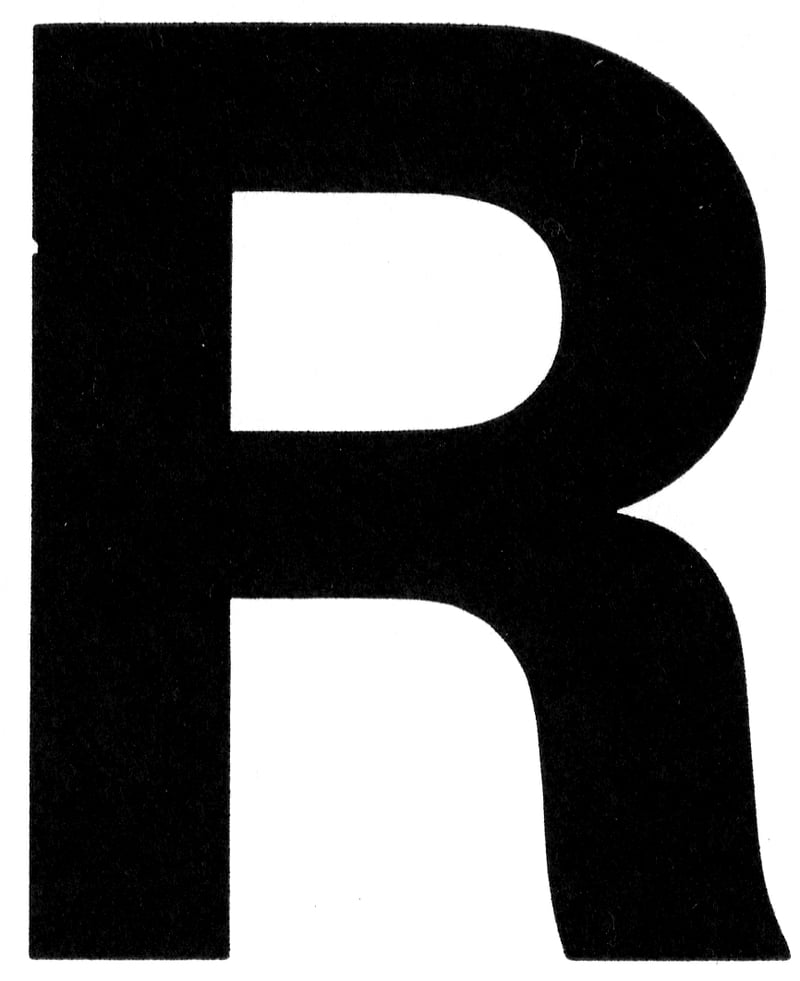
Helvetica Plakat
Grösse: 240 pt
Druckmuster mit Text «GR8»
Klassifizierung
Sans Serif
Schriftschnitt
Plakat
Design
Max Miedinger
Jahr
1957
Schriftgiesserei
Haas
Helvetica Plakat wurde von der Haas’schen Schriftgiesserei AG in Münchenstein in Holz, Kunststoff und Hartaluminium in den Grössen 6 bis 40 Cicero vertrieben.